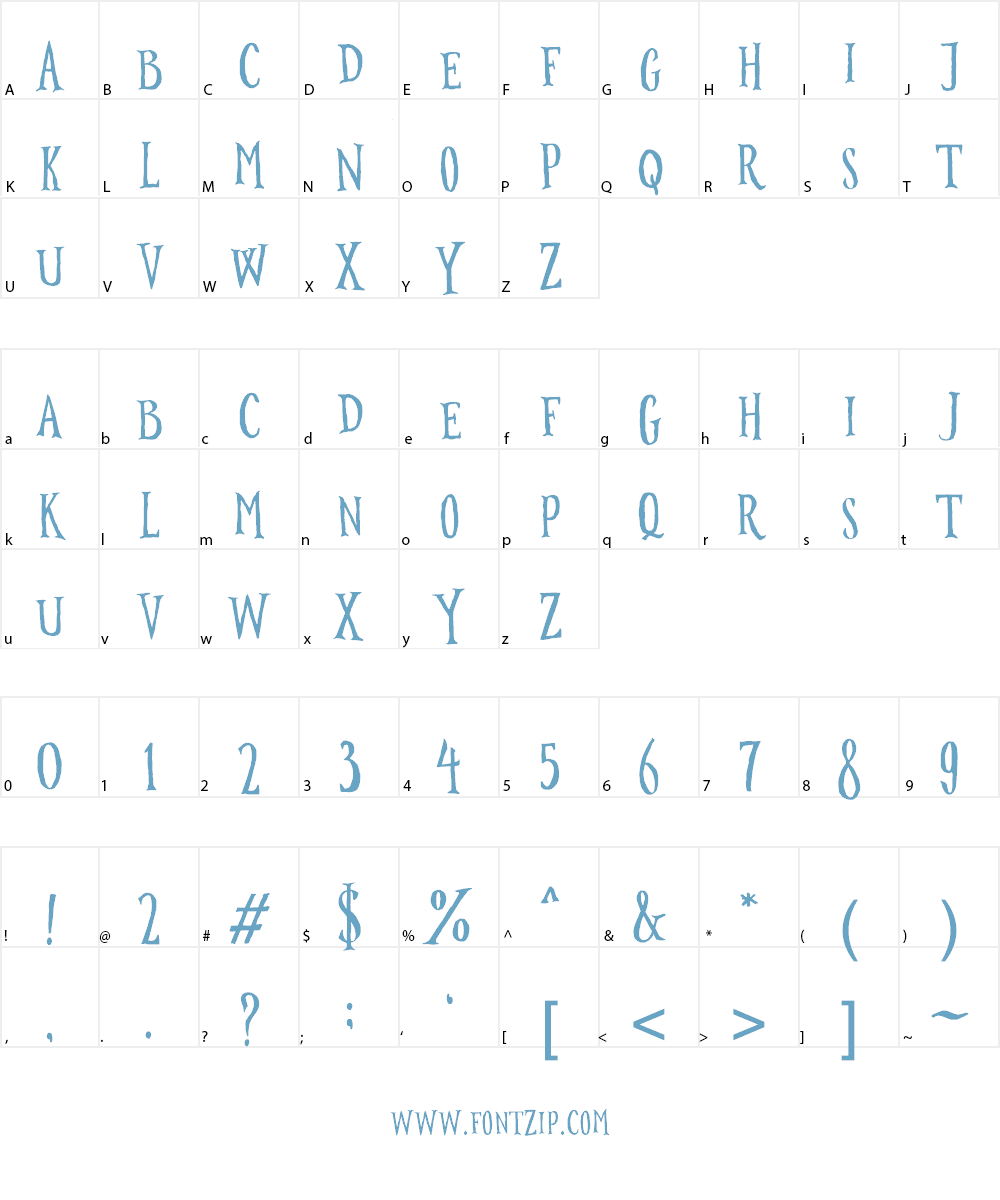
Surabanglus diambil dari judul salah satu cerita pendek Ahmad Tohari dalam bukunya "Senyum Karyamin". Surabanglus sendiri adalah nama dari sejenis ketela yang beracun jika dimakan.
Surabanglus taken from the title of a short story Ahmad Tohari in his book " Smile Karyamin " . Surabanglus itself is the name of a type of yam which is toxic if eaten .